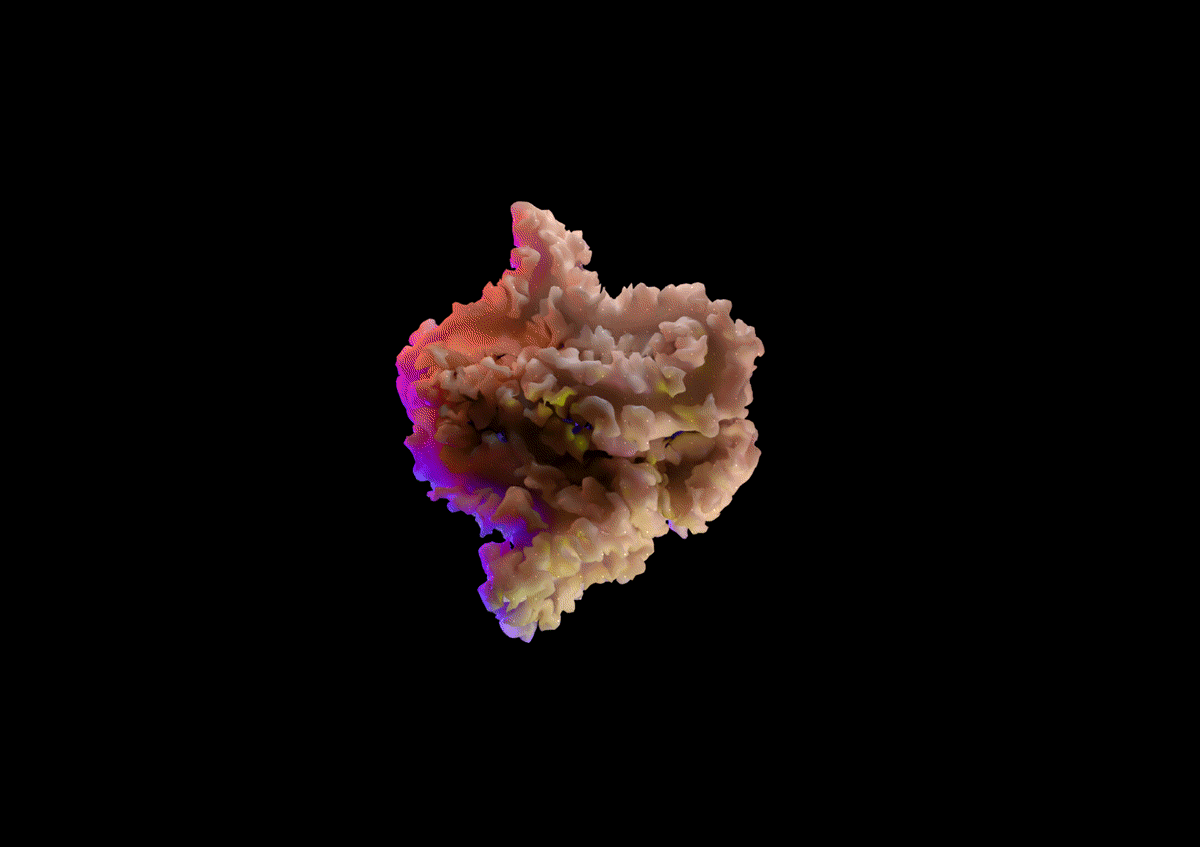
El diseñador de origen alemán Oliver Latta; el cual, se ha inspirado en la vida marina de los arrecifes para el diseño de esta genial serie tipográfica.
Esta serie nos muestra cada diseño inspirado en colores y texturas muy propias de los corales que habitan en los arrecifes marinos; razón por la cual, te dejo con algunas fotografías del trabajo de este diseñador, el cual, espero que disfrutes.
Tipografía inspirada en la vida marina